Ponad 10 najlepszych czcionek Shopify dla Twojego sklepu
Zakupy online powinny być ekscytujące! Jako sprzedawca internetowy Twoim celem jest ułatwienie prostych i przyjemnych zakupów. Twoi klienci nie powinni być zmuszeni do przeszukiwania stron sklepu Shopify w poszukiwaniu niezbędnych produktów pośród niepowiązanych treści.
Sfrustrowani klienci po prostu opuszczą Twoją witrynę, jeśli nie będą mogli od razu znaleźć tego, czego szukają. Dlatego powinieneś spróbować poprawić wrażenia użytkownika.
Wspaniałe wrażenia użytkownika obejmują kroje pisma, dlatego dzisiaj podzielimy się z Tobą ponad 10 najlepszymi czcionkami Shopify, które pomogą Ci w opracowaniu idealnej strategii dotyczącej czcionek dla Twojej firmy online.
Dlaczego czcionki są ważne dla Twojego sklepu Shopify?
Czcionki są niezbędne w każdym biznesie e-commerce, ponieważ nakłonienie konsumentów do przeczytania treści jest trudne. Dlatego liczy się każde słowo, a przyciągnięcie użytkowników ma kluczowe znaczenie.
Czcionki określają, w jaki sposób Twoi odbiorcy postrzegają Twój sklep, ponieważ wyrażają określone myśli, uczucia i zachowania w oparciu o ich projekt. Wybór interesującego kroju pisma zatrzyma użytkowników na Twojej stronie na dłużej, przyciągnie ich do treści, poprawi ich zapamiętywanie i, miejmy nadzieję, poprowadzi ich przez proces zakupu. Na przykład czcionki szeryfowe, takie jak Times New Roman i Garamond, również mogą zwiększyć szybkość czytania.
Odpowiednio użyte czcionki przenoszą oko z jednego miejsca do drugiego w zamierzonej kolejności. Ponadto stosowanie przyciągających wzrok czcionek w nagłówkach i banerach promocyjnych pomaga zwrócić uwagę na to, co chcesz promować.
Podsumowując, gdy właściciele sklepów Shopify, a także właściciele innych firm, odpowiednio wykorzystują czcionki, mogą pomóc kupującym online łatwiej zapamiętać Twoją markę i pozytywnie wpłynąć na sprzedaż i przychody.
O czym należy pamiętać przy wyborze czcionek do sklepu Shopify?
Wybierając najlepsze czcionki Shopify dla swojego sklepu internetowego, należy wziąć pod uwagę aspekty wymienione poniżej.
Używaj nie więcej niż 3 czcionek w swojej witrynie Shopify
Najważniejszą rzeczą, o której właściciele firm powinni pamiętać, jest to, że na stronie internetowej powinny znajdować się tylko trzy główne czcionki: jedna dla nagłówków, jedna dla tekstu podstawowego i jedna dla akcentów.
Użyj podstawowej czcionki, czyli tej, która jest najbardziej zauważalna, dla wszystkich tytułów, banerów i nagłówków (duży tekst).
używana jako dodatkowa czcionka dla mniejszego tekstu podstawowego. To powinna być czcionka, która jest najbardziej czytelna.Ta czcionka jest używana na stronie jako akcent dla poszczególnych elementów, takich jak przyciski. Logo marki może być w tej czcionce.
Spróbuj użyć standardowych czcionek
Witryny do osadzania czcionek (takie jak Google Web Fonts lub Typekit) oferują wiele kreatywnych czcionek, które mogą dodać coś nowego, świeżego i zaskakującego do Twoich projektów. Co więc może pójść nie tak? W rzeczywistości ta metoda ma jedną poważną wadę: atrakcyjne czcionki mogą odwracać uwagę konsumentów od czytania. Ludzie mogą spędzać czas zastanawiając się nad czcionkami używanymi przez projektantów, zamiast czytać tekst.
Jeśli nie masz istotnej potrzeby posiadania niestandardowej czcionki, takiej jak branding lub tworzenie immersyjnych wrażeń, zazwyczaj zaleca się trzymanie się czcionek systemowych. Pamiętaj, że dobra typografia kieruje uwagę czytelnika na tekst, a nie na samą czcionkę.
Wybierz czcionkę, która działa dobrze w różnych rozmiarach
Twoja witryna będzie dostępna dla użytkowników korzystających z urządzeń o różnych rozmiarach i rozdzielczościach ekranu. Większość interfejsów użytkownika wymaga elementów tekstowych o różnej wielkości (kopia przycisku, etykiety pól, nagłówki sekcji itp.). Aby zachować czytelność i użyteczność we wszystkich rozmiarach, wybierz krój pisma, który dobrze sprawdza się w wielu rozmiarach i gramaturach.
Sprawdź, czy wybrany krój pisma jest czytelny na małych ekranach! Unikaj krojów pisma z kursywą, takich jak Vivaldi (w przykładzie poniżej): są atrakcyjne, ale trudne do odczytania.
Używaj czcionek, które mają rozpoznawalne litery
Kilka czcionek, zwłaszcza te z literami „i” i „L”, sprawia, że zbyt łatwo jest źle zrozumieć podobne formy liter. Dlatego wybierając czcionkę, pamiętaj o przetestowaniu jej w różnych scenariuszach, aby upewnić się, że nie będzie stanowić problemu dla Twoich konsumentów.
Kategorie czcionek
Czcionka wybrana dla witryny Shopify stanowi podstawę jasnej komunikacji treści internetowych. Zasadniczo istnieją 3 główne typy czcionek, a mianowicie Serif, Sans-serif.
- Czcionki szeryfowe: ta czcionka ma małe stopki lub ogonki na końcach kresek w kształcie litery. Times New Roman lub Georgia to dwa typowe przykłady tego kroju pisma.
- Czcionki bezszeryfowe: nie ma szeryfów, dodatkowych końcówek ani stopek na końcu każdej litery w tej czcionce. Czcionki bezszeryfowe są często używane do zwykłego pisania tekstu. Czcionki Sans Serif to Arial, Futura i Helvetica.
Jak wybrać najlepsze czcionki Shopify dla swojego sklepu?
Być może eksperymentujesz z kilkoma czcionkami Shopify, aby zobaczyć, które najlepiej pasują do stron internetowych Twojej firmy.
To ważne pytanie, a wymienione poniżej czynniki pomogą Ci wybrać idealny krój pisma dla sklepów Shopify:
- Podstawowa idea i duch Twojej firmy
- Wrażenie, które próbujesz wywołać, aby zaimponować potencjalnym konsumentom
- Twoja marka opiera się na wartościach
- Pożądane emocje dla klienta
- Tego rodzaju pytania mogą pomóc i skierować Cię we właściwym kierunku.
Oprócz powyższych podstawowych pytań, przy wyborze najlepszych czcionek Shopify należy również wziąć pod uwagę następujące elementy.
Rozmiary czcionek
Różne wagi mogą wskazywać na różne osobowości marki. Czcionki, które są cieńsze i bardziej stylizowane, generalnie kojarzą się z modernizmem, minimalizmem i elegancją. Jednak kiedy kroje pisma stają się grubsze, zaczynają wyglądać na bardziej swobodne, hałaśliwe, a nawet ekstrawertyczne.
Czcionki, które uzupełniają lub kontrastują
Czcionki uzupełniające uzupełniają się nawzajem, nie powodując zbytniego konfliktu lub kontrastu.
Na przykład możesz sparować pogrubiony krój nagłówka z tą samą czcionką o zwykłej grubości. Wskazuje to na harmonię i równowagę.
Kontrastujące kombinacje czcionek to coś, co należy wziąć pod uwagę. Pod względem kształtu, grubości, stylu i wyrównania te dwa kroje pisma są diametralnie różne.
Powszechną techniką łączenia kontrastujących krojów pisma jest użycie czcionki bezszeryfowej jako podstawowego kroju pisma i czcionki szeryfowej jako czcionki pomocniczej.
Ponad 5 najlepszych czcionek Shopify dla Twojego sklepu internetowego
Rzućmy okiem na czcionki dostępne dla Twojego sklepu Shopify. Pamiętaj, że możesz użyć dowolnych innych czcionek, których nie ma na tej liście, a nawet dodać niestandardowe czcionki do sklepu Shopify; są to po prostu najbardziej popularne i przyjazne dla czytelnika czcionki.
Helvetica
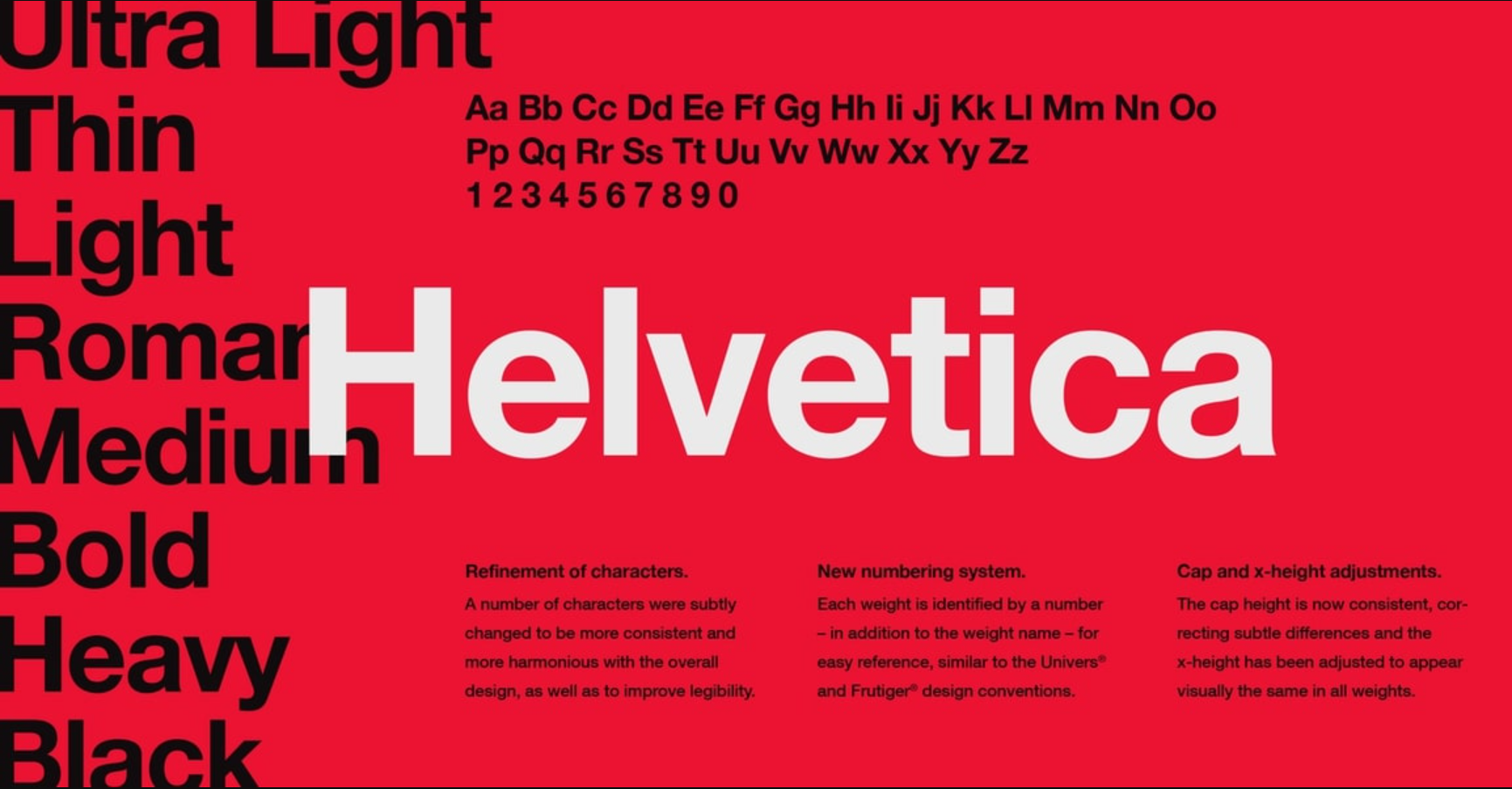
Helvetica istnieje od 1957 roku. Ponieważ należy do rodziny bezszeryfowych, litery nie mają krzywizn na końcach każdej kreski. Jest to klasyczna czcionka, która jest teraz dostępna w różnych stylach, w tym Helvetica lite, zaokrąglona i nie tylko.Helvetica to podstawowa czcionka często używana przez duże korporacje do tworzenia logo i materiałów marketingowych. Co więcej, Helvetica to prosta, atrakcyjna czcionka, która pasuje do każdego projektu. Pasuje do niego każda czcionka kaligraficzna, ozdobna lub pismo odręczne.
Garamond
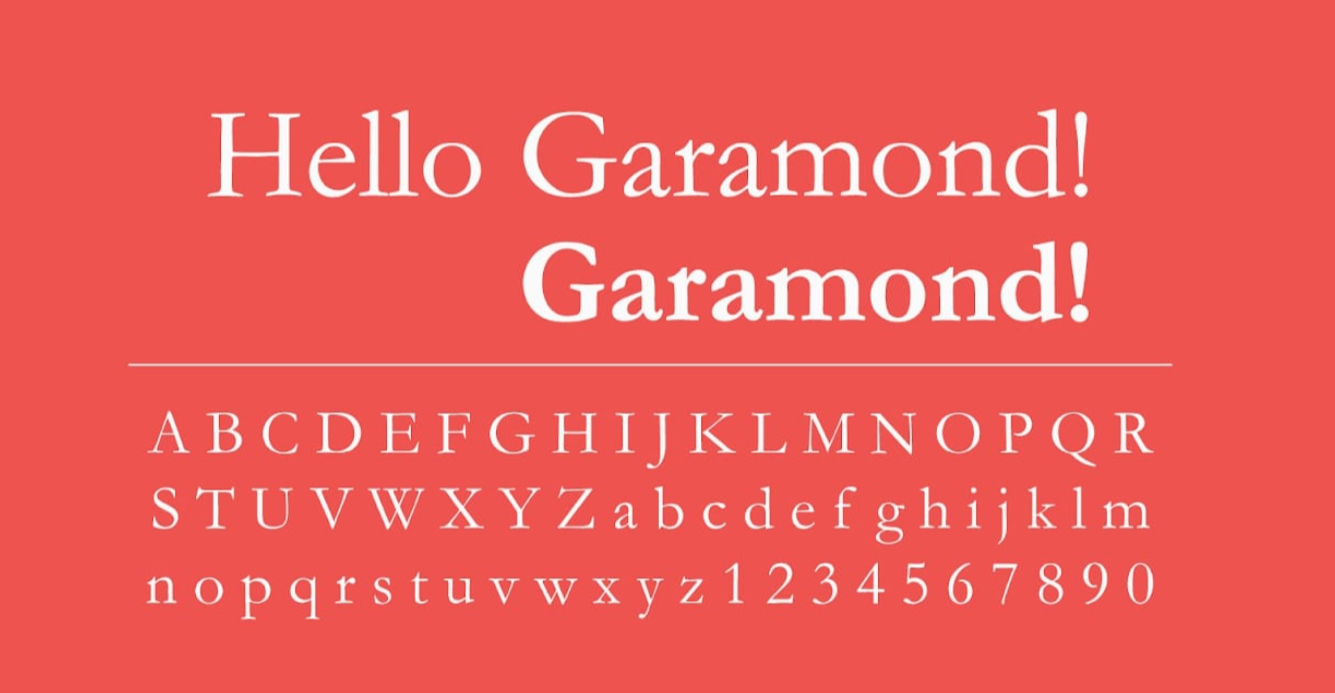
Garamond to kolejna starożytna czcionka w stylu retro. Jest idealny do tekstu podstawowego w publikacjach drukowanych, a ponadto jest łatwy do odczytania. Dzięki temu krojowi Twoja witryna będzie miała ponadczasowy charakter, a każda litera może wydawać się grawerowana.Arial
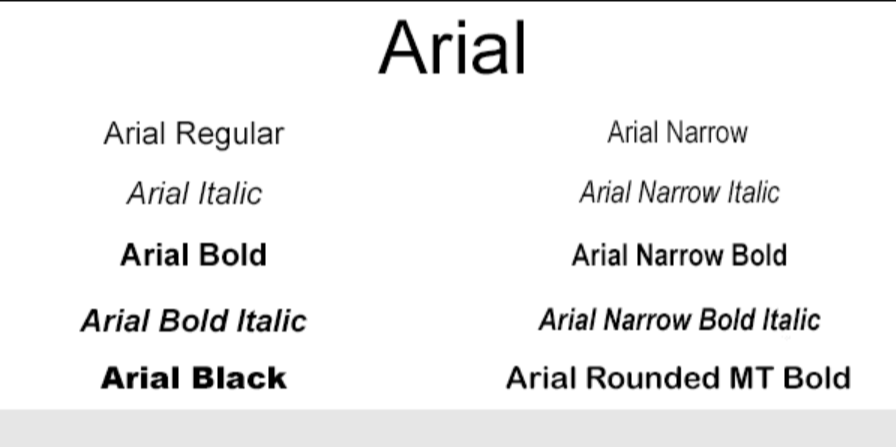
Arial jest prawdopodobnie najbezpieczniejszą czcionką do wyboru i jest prawie standardem branżowym w dziedzinie typografii. Arial jest znany jako Arial MT w niektórych urządzeniach lub edytorach tekstu. Są identyczne bez zauważalnych różnic.Ta czcionka ma kilka wariantów, ale wszystkie są łatwe do odczytania. Należy do rodziny czcionek bezszeryfowych. Sans serif oznacza, że na końcu każdej litery nie ma linii. Ta czcionka jest dobrze znana i jest zawarta w systemie operacyjnym wszystkich urządzeń Microsoft. Ta czcionka jest również rozpoznawana przez systemy iOS i Android.
Verdana
Kilku specjalistów od czcionek uważa, że Verdana to prawdziwy krój pisma internetowego. Jest to prosta czcionka bezszeryfowa, która jest wystarczająco duża, aby ułatwić czytanie. Jeśli przyjrzysz się uważnie, zauważysz, że litery są nieco wydłużone, co ułatwia ich czytanie na laptopach, tabletach i smartfonach. Verdana koncentruje się teraz na urządzeniach mobilnych i komputerach PC. I odpowiednio, biorąc pod uwagę, że został stworzony dla i przez Microsoft.Kalibr
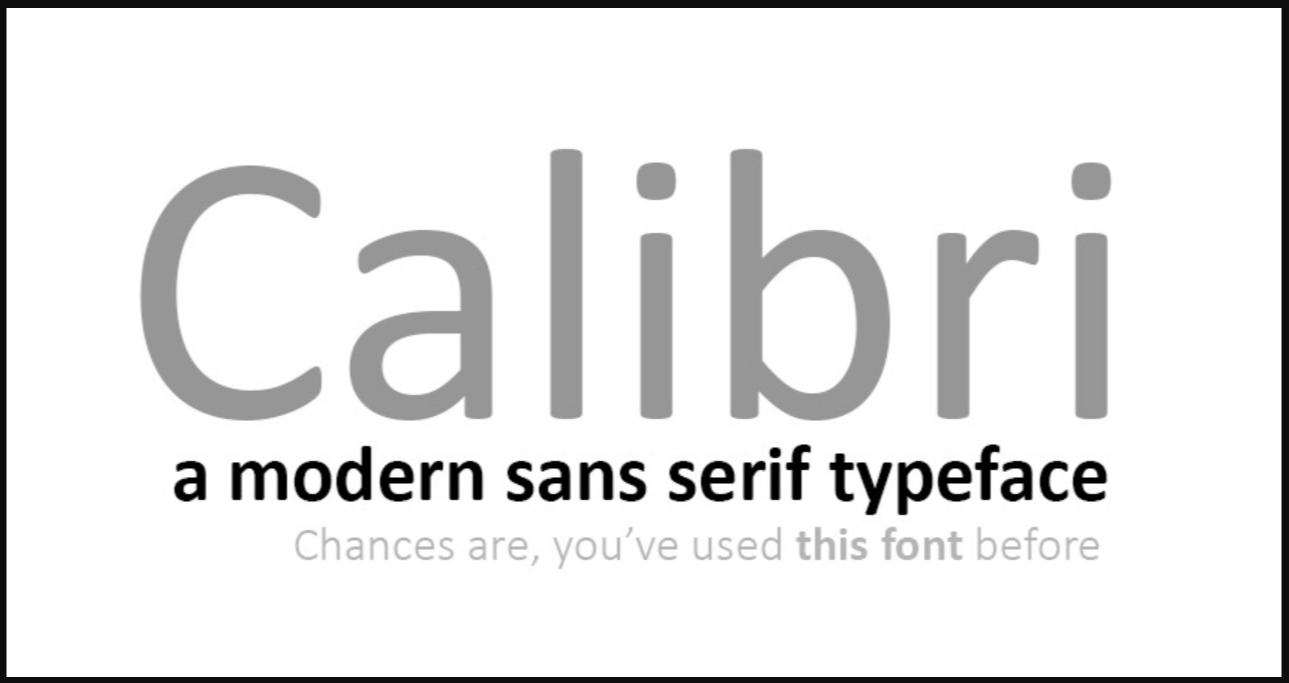
Ten jest bardzo nowy, został wydany w 2004 roku i udostępniony publicznie w 2007 roku. Microsoft przedstawił go światu i uczynił domyślnym krojem pisma dla Microsoft Word i innych produktów MS Office. Jest zaokrąglony, więc nie męczy oczu. Chociaż jest okrągły, nie przypomina kreskówki. Ma formalny wygląd i jest uważany za prosty styl kroju pisma.Roboto regularne
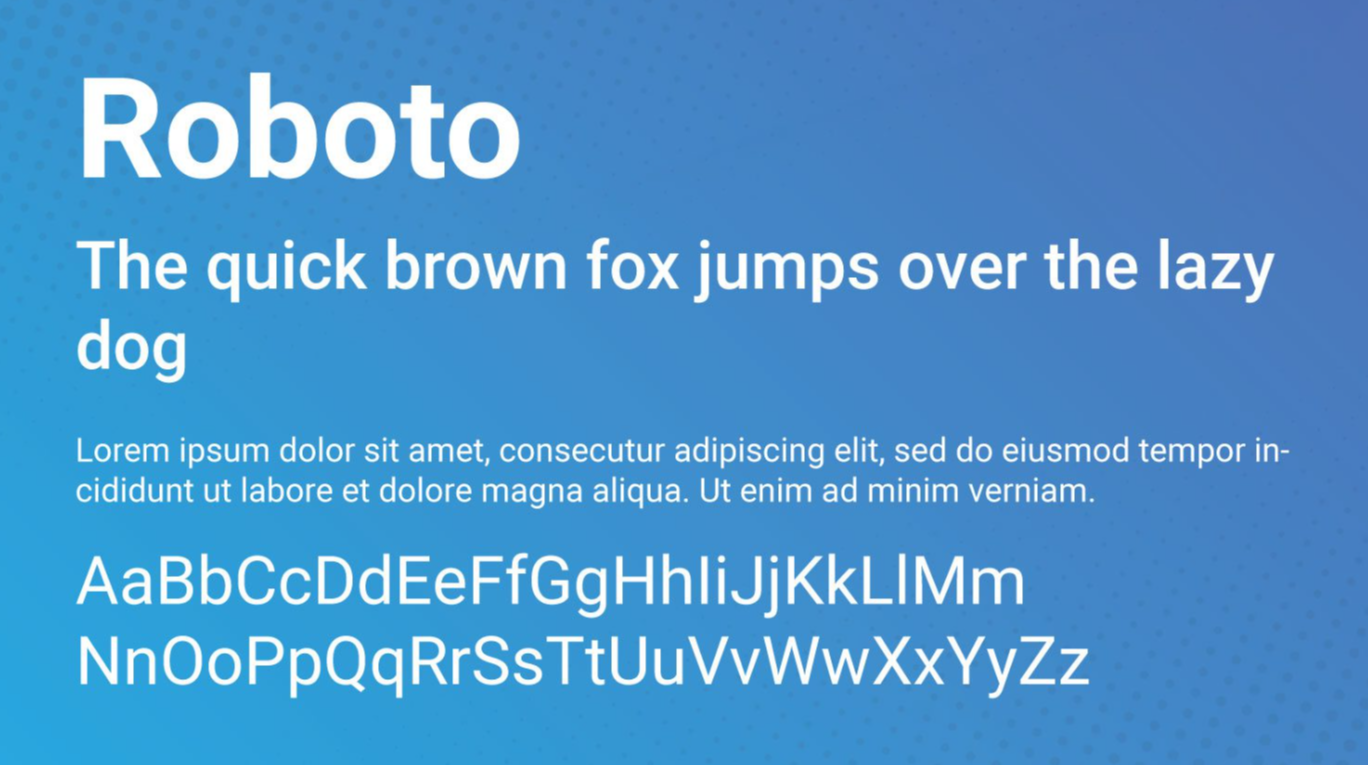
Roboto (Regular) to czcionka uniwersalna. Jest to prosta geometryczna czcionka, która sprawdzi się w praktycznie każdym projekcie. Ma również doskonałe krzywe i jest powszechnie uważany za bardzo łatwy do odczytania. Od 2014 roku służy jako krój pisma dla systemu operacyjnego Google Android. Działa dobrze z ozdobnymi czcionkami pisma, jak również ze standardową czcionką szeryfową.Otwórz Sansa
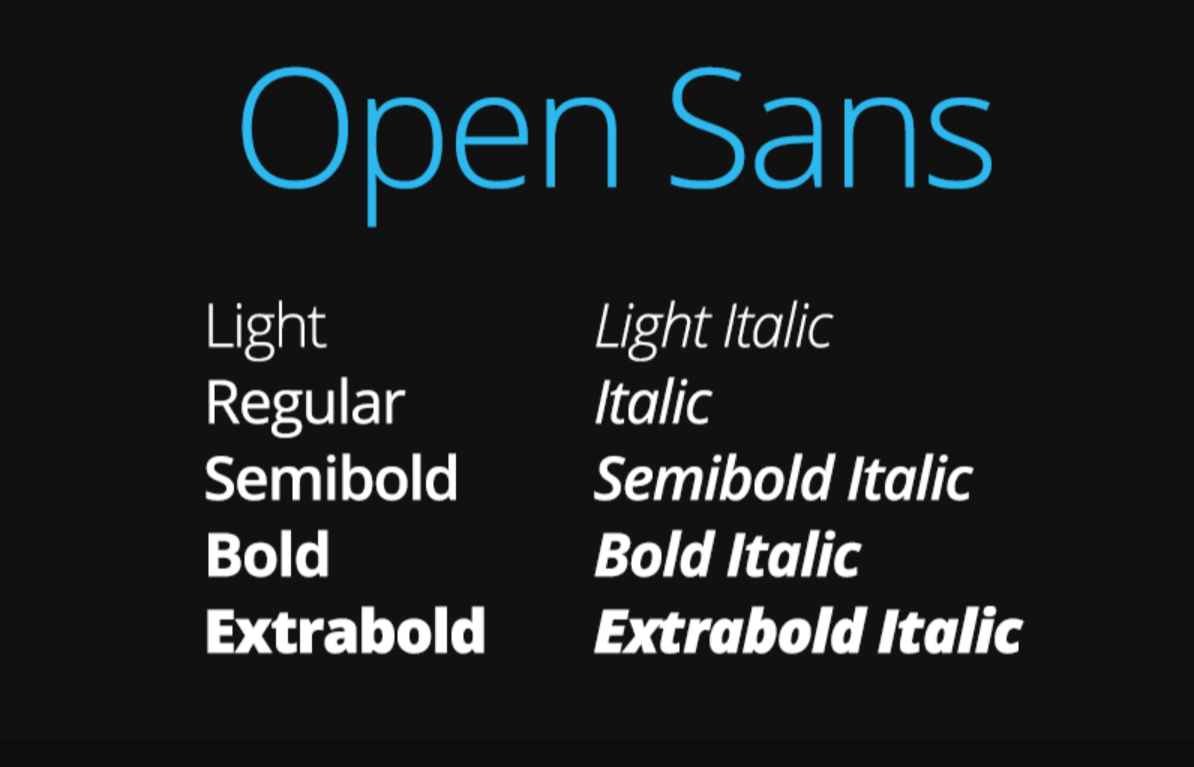
Open Sans to minimalistyczna czcionka, która uzupełni każdą czcionkę ozdobną lub skryptową. Dowolna czcionka kaligraficzna w połączeniu z Open Sans to zwycięska kombinacja dla biżuterii lub ręcznie robionych przedmiotów. To jedna z najlepszych czcionek sklepu Shopify.Czcionka Times New Roman
Ta czcionka jest skromną modyfikacją czcionki Times (jednej z najstarszych czcionek). Jest często używany i łatwo rozpoznawalny w gazetach i czasopismach na całym świecie. Tym krojem pisanych jest również kilka powieści, a ludzie z całego świata nie będą mieli problemu z ich przeczytaniem.Nazwa Times została nadana czcionce, ponieważ została zaprojektowana dla Time Magazine w 1931 roku. Chociaż magazyn już jej nie używa, nadal jest regularnie wykorzystywana jako tekst podstawowy w produkcjach gazet reklamowych.
Kambria
Cambria wygląda świetnie i jest lepsza, jeśli nie chcesz używać Calibri. Należy do rodziny szeryfów, co oznacza, że litery mają kilka linii na końcach. Niemniej jednak uznaje się, że jest to prosta forma czcionki. Cambria najlepiej sprawdza się jako dokument podstawowy, ponieważ jest wyjątkowo czytelna nawet przy niewielkich rozmiarach.Uderzenie
Jest to popularna czcionka nagłówków. Jest gęsty, śmiały i łatwy do odczytania, z dużym nagłówkiem. Krój pisma najlepiej sprawdza się w przypadku tytułów i napisów, ale nie w przypadku tekstu. W przypadku nadmiernego użycia szerokość czcionki może utrudniać czytanie. Najlepiej wykorzystać go do ogłoszenia oferty lub przyciągnięcia uwagi odwiedzających w swoich reklamach.
Jakie są najlepsze czcionki Shopify dla Twojego sklepu?
Najlepsze sklepy z czcionkami Shopify to takie, które są zarówno łatwe do odczytania, jak i mają profesjonalny wygląd. Chociaż istnieje wiele krojów pisma do wyboru, zalecamy trzymanie się czcionek bezszeryfowych, takich jak Roboto, Verdana, Arial i Calibri, które są szeroko stosowane w Internecie.
Te kroje pisma są świetną opcją dla tytułów, nagłówków i witryn e-commerce.
Podsumowując, niezależnie od tego, jaką czcionkę wybierzesz dla swojego sklepu Shopify, upewnij się, że jest ona czytelna i wygląda dobrze na wszystkich urządzeniach, abyś mógł cieszyć się dobrymi zakupami i zyskać więcej pozytywnych recenzji dla swojego sklepu.